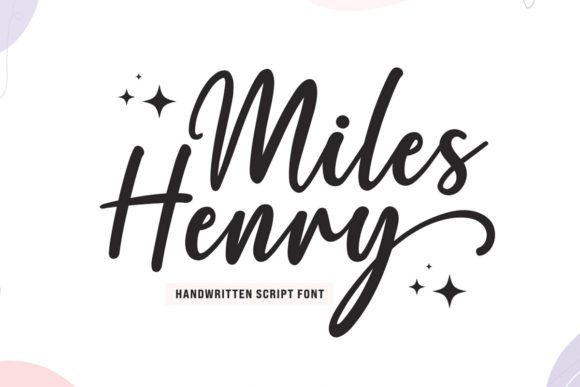
Miles Henry
適切なデザイン要素を見つけるのは難しい場合がありますが、Miles Henryは作品を即座に引き立てる優れたコレクションを提供します。
POD(オンデマンド印刷)製品、結婚式の招待状、またはソーシャルメディアのグラフィックを作成している場合でも、Miles Henryは理想的です。